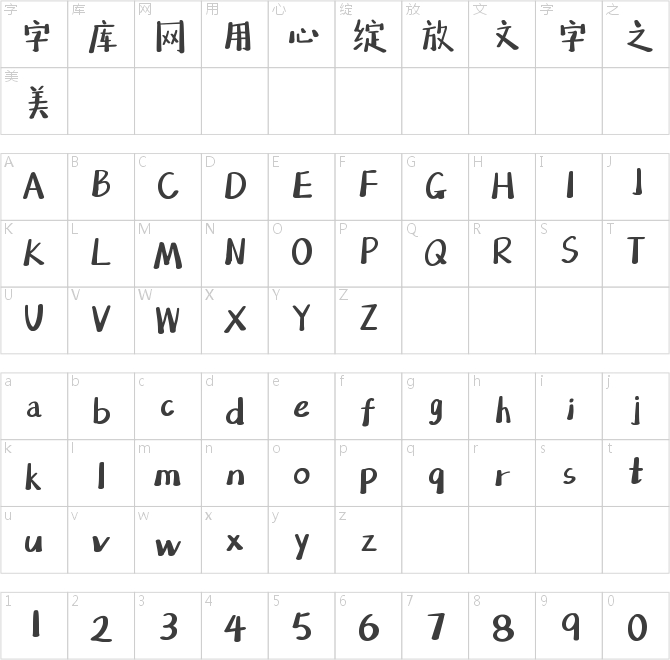
字魂195号-萌趣百奇体
字魂195号-萌趣百奇体是一款手写字。字形圆润修长,字体的结构灵活,笔画错落有致,字体风格有趣而富有个性,适用于品牌广告设计和产品包装设计。
字魂195号-萌趣百奇体字体zihun195hao-mengqubaiqiti字库是一款让人赏心悦目、百看不厌的中文字体,适合各类广告和产品包装设计应用,字体大小9.81MB,格式为ttf字体,上传用户是尚永科技,作者/版权方为字魂